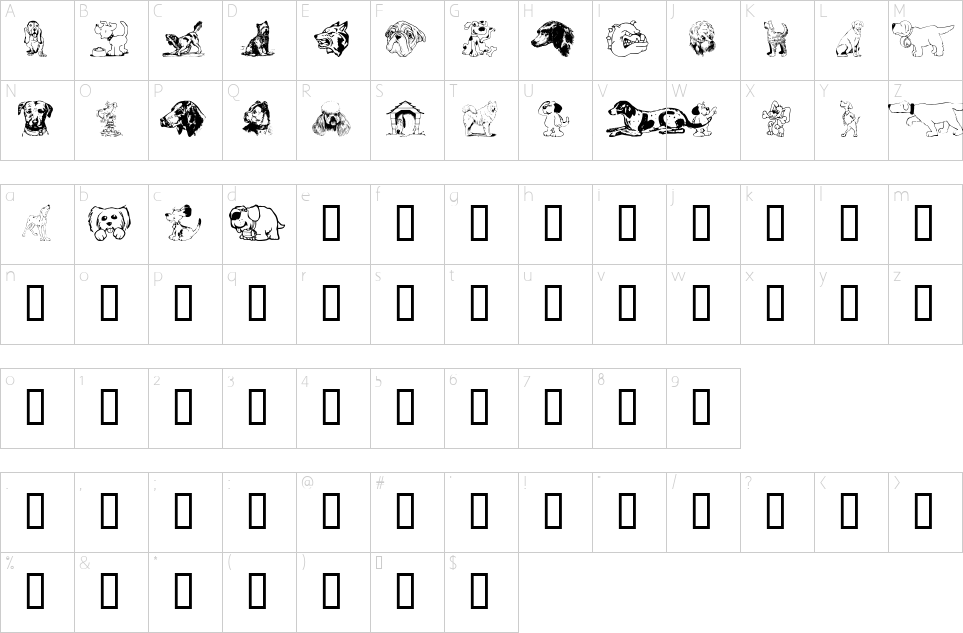
Dogg Art Font – Download Grátis
Descubra a riqueza de detalhes e a expressividade única da Dogg Art font. Este estilo vibrante e irreverente foi criado pela Gem Fonts, com uma variedade de formas e efeitos que tornam a Dogg Art font perfeita para qualquer projeto de design gráfico. Com seu design inteligente e fácil de usar, Dogg Art font é a escolha perfeita para os designers que buscam uma fonte moderna e descontraída. Gravada para sistemas Windows e Mac, Dogg Art font é um download seguro que vai adicionar um toque único e irreverente ao seu design. Com mais de 70,000 downloads, é claro que essa font se destaca como um recurso gráfico indispensável. Experimente Dogg Art font e veja por si mesmo por que tantos designers já a usam em seus projetos.